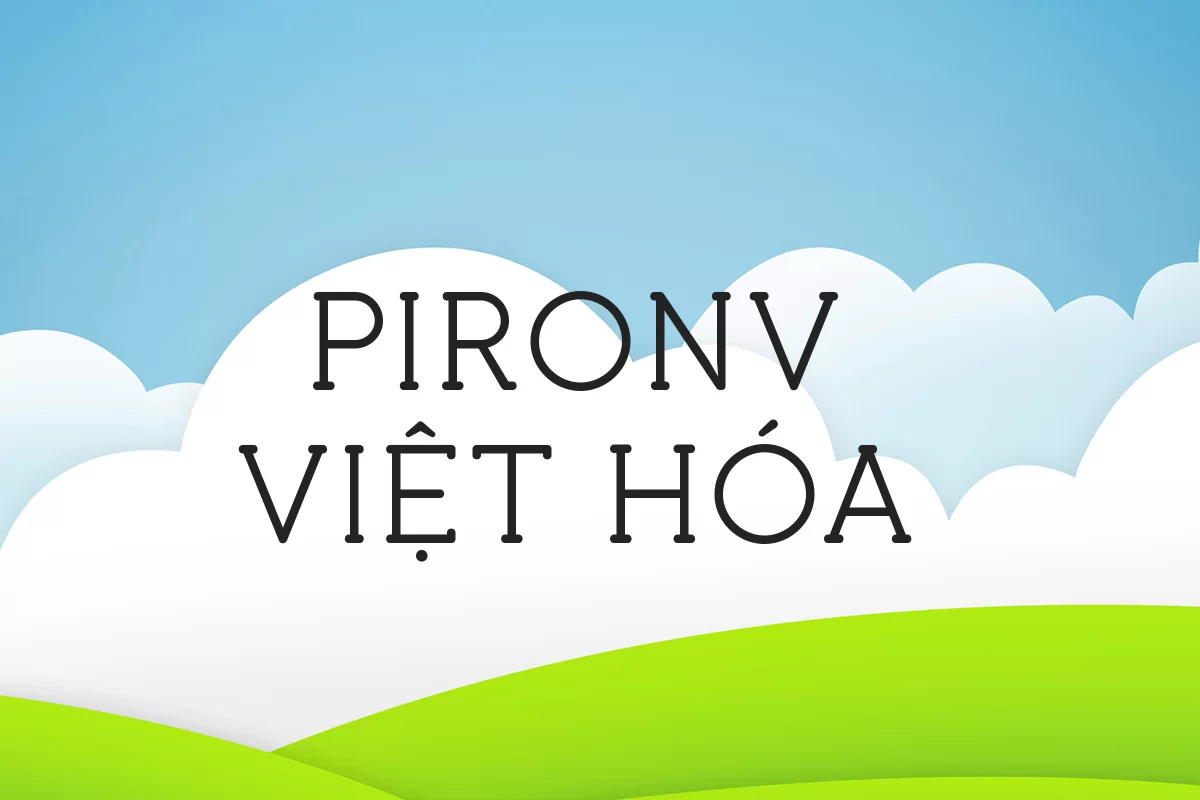
Piron là một kiểu chữ sans-serif mang đậm chất hình học, hiện đại và tối giản nhưng lại được nhấn nhá bởi những chi tiết bo tròn nhẹ ở đầu nét, tạo nên cảm giác tinh tế và dễ tiếp cận. Các ký tự của Piron được thiết kế cân đối, đường nét thanh mảnh, phù hợp cho cả tiêu đề lẫn văn bản ngắn trong thiết kế đồ họa, poster, bìa sách hay nhận diện thương hiệu.
Phiên bản Piron Việt hóa giữ trọn vẹn tinh thần thiết kế gốc, đồng thời được bổ sung đầy đủ dấu tiếng Việt, đảm bảo trải nghiệm sử dụng nhất quán và chuyên nghiệp cho cộng đồng sáng tạo trong nước.
Đây là lựa chọn lý tưởng cho các nhà thiết kế yêu thích sự đơn giản nhưng vẫn muốn tạo điểm nhấn độc đáo trong từng con chữ.
Phiên bản Piron Việt hóa giữ trọn vẹn tinh thần thiết kế gốc, đồng thời được bổ sung đầy đủ dấu tiếng Việt, đảm bảo trải nghiệm sử dụng nhất quán và chuyên nghiệp cho cộng đồng sáng tạo trong nước.
Đây là lựa chọn lý tưởng cho các nhà thiết kế yêu thích sự đơn giản nhưng vẫn muốn tạo điểm nhấn độc đáo trong từng con chữ.